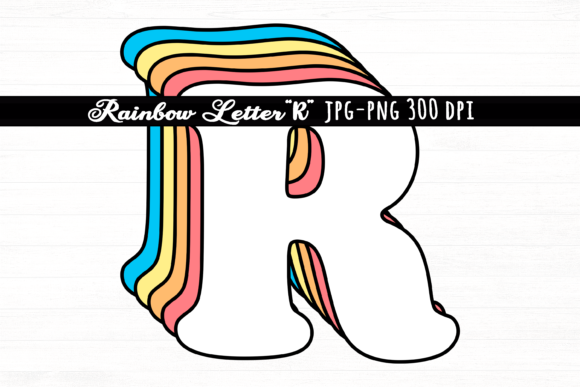
Letter R Rainbow Initial Cute Retro Font
Mencari elemen desain yang tepat bisa jadi sulit, namun Letter R Rainbow Initial Cute Retro Font menawarkan koleksi luar biasa yang akan langsung meningkatkan kualitas karya Anda.
Dibuat dengan presisi, Letter R Rainbow Initial Cute Retro Font menyediakan vektor yang bersih, tipografi yang halus, serta lisensi komersial untuk ketenangan pikiran Anda.
Baik Anda membuat produk POD (Print on Demand), undangan pernikahan, atau grafis media sosial, Letter R Rainbow Initial Cute Retro Font adalah pilihan yang sangat ideal.